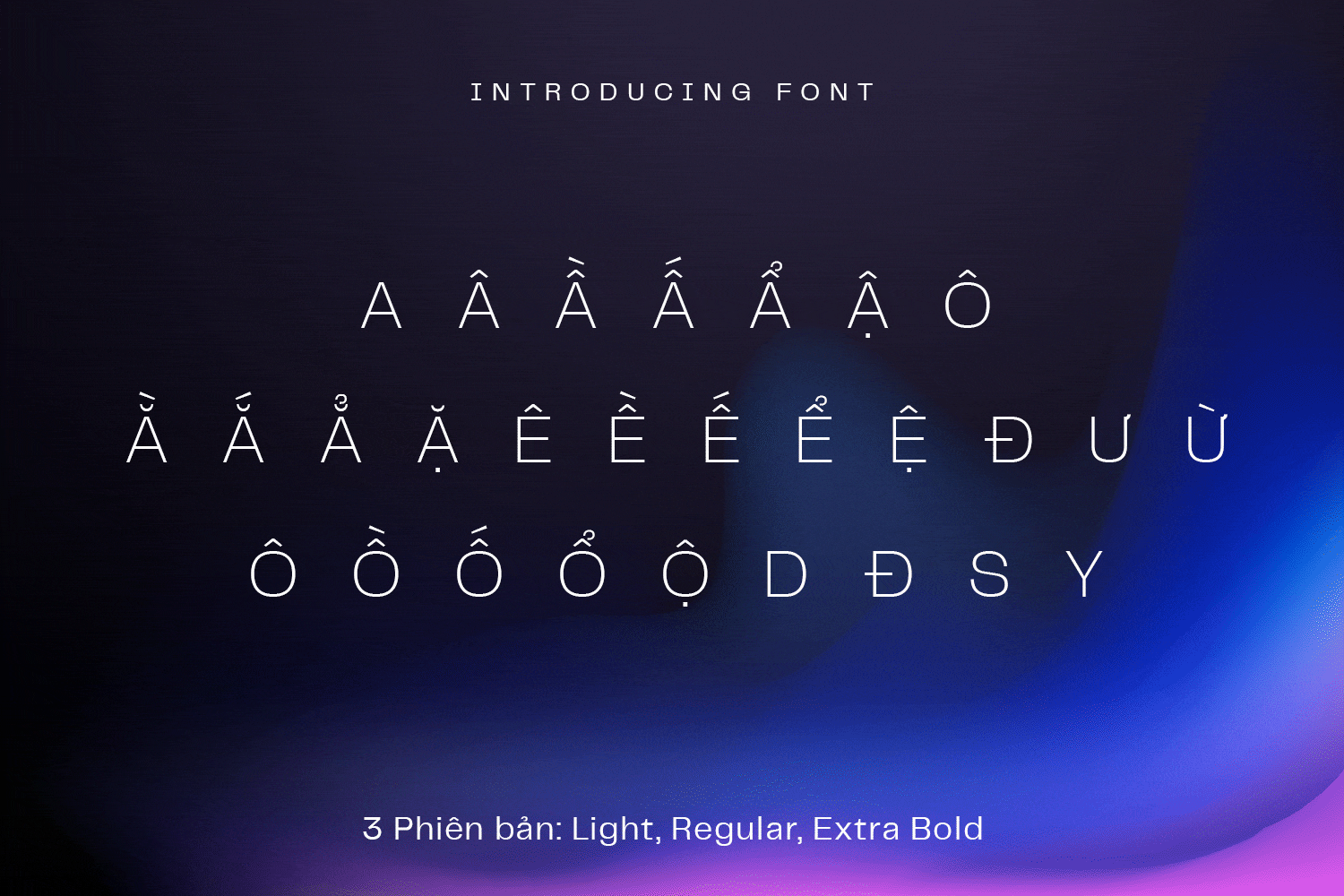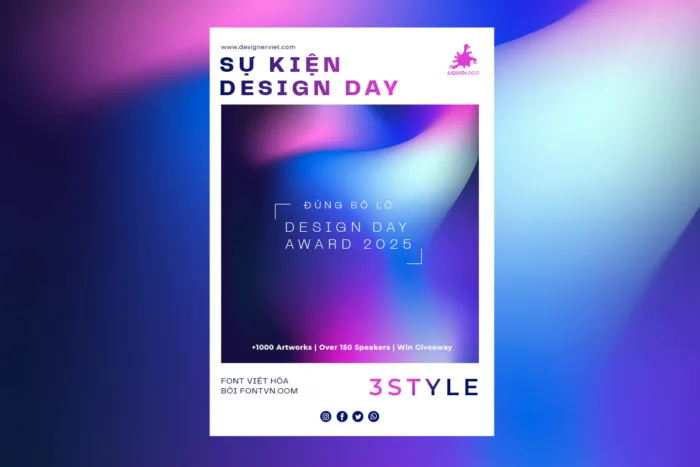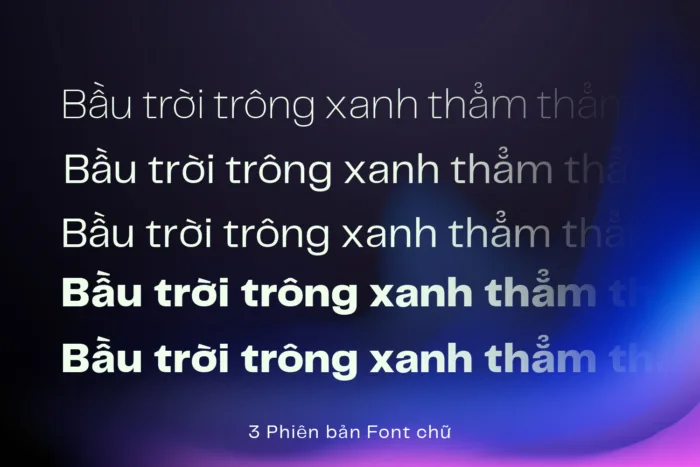
DVN Telegraf Việt hóa – Font chữ tuyệt đẹp cho thiết kế (3 Style)
DVN Telegraf Việt hóa là một phông chữ hiện đại mang phong cách sans-serif, phù hợp với xu hướng thiết kế đương đại. Font có dáng chữ gọn gàng, thanh thoát và dễ đọc, thể hiện sự chuyên nghiệp và tinh tế trong từng dòng chữ. Nhờ vào việc Việt hóa đầy đủ, DVN Telegraf có thể sử dụng linh hoạt cho nhiều mục đích khác nhau như thiết kế thương hiệu, giao diện web, bài thuyết trình hoặc ấn phẩm in ấn. Với hệ thống trọng lượng đa dạng, font giúp người dùng dễ dàng phối hợp để tạo điểm nhấn và cấu trúc rõ ràng cho nội dung. Đây là lựa chọn lý tưởng cho những ai đang tìm kiếm một kiểu chữ hiện đại, tối giản nhưng vẫn mang tính ứng dụng cao.
Phiên bản Việt hóa bao gồm 3 Style: Light, Regular, Extra Bold